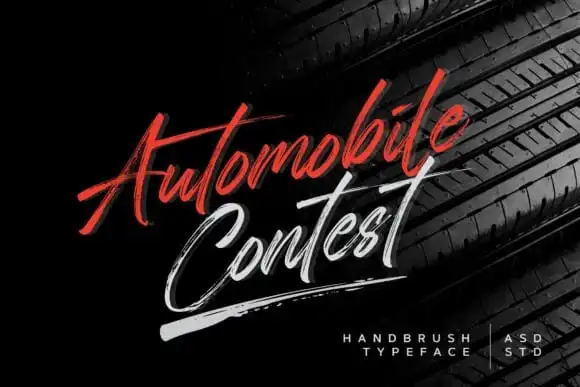
Automobile Contest Brush Font
A Automobile Contest Brush Font é uma fonte cursiva que oferece um estilo artesanal realista. Ela imita perfeitamente a aparência de desenhos manuais, trazendo uma autenticidade única e vibrante. Esta fonte foi criada pelo Asd Studio, e é ideal para desenvolver qualquer tipo de design onde se deseja incorporar um elemento de arte manual e moderno. É especialmente adequada para o branding da sua marca, embalagens de produtos, convites, citações, camisetas, rótulos, outdoors e logotipos. Com seu estilo elegante e versátil, esta fonte é perfeita para aqueles que buscam adicionar um toque criativo a seus projetos visuais, tornando-os ainda mais chamativos e autênticos.